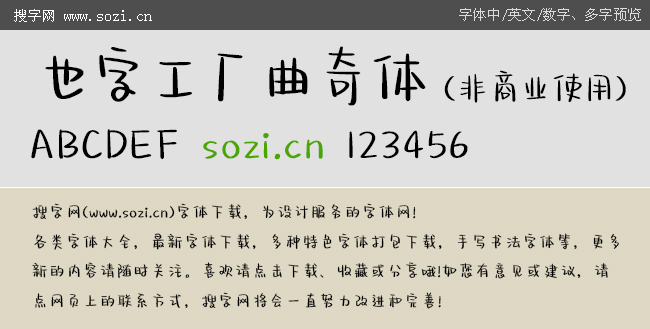
也字工廠曲奇體
搜字網給大家提供一款也字工廠曲奇體(非商業使用)中文字體下載,也字工廠曲奇體是一款略帶卡通風格的手寫字體,字體書寫自然流暢,又帶有一點趣味性,具有很好的視覺效果。適合應用于兒童繪本、兒童海報、網頁設計等應用(此字體為個人非商用版,商用可以聯系:官方網址:https://yefont.com/home,聯系方式:13798980448)。